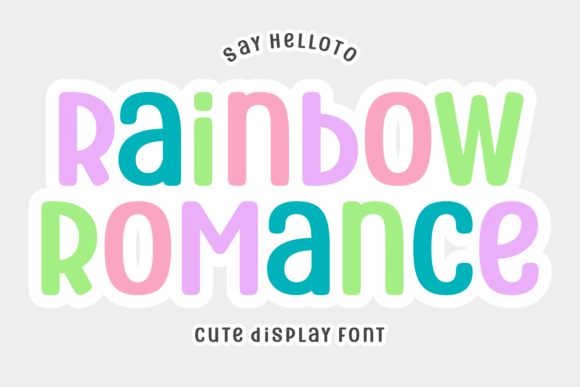
Rainbow Romance
สร้างขึ้นอย่างแม่นยำ Rainbow Romance ให้เวกเตอร์ที่สะอาด พิมพ์ตัวอักษรที่ราบรื่น และใบอนุญาตเชิงพาณิชย์เพื่อความสบายใจ
ไม่ว่าคุณจะสร้างผลิตภัณฑ์ POD (Print on Demand) คำเชิญงานแต่งงาน หรือกราฟิกโซเชียลมีเดีย Rainbow Romance ก็เหมาะสมอย่างยิ่ง